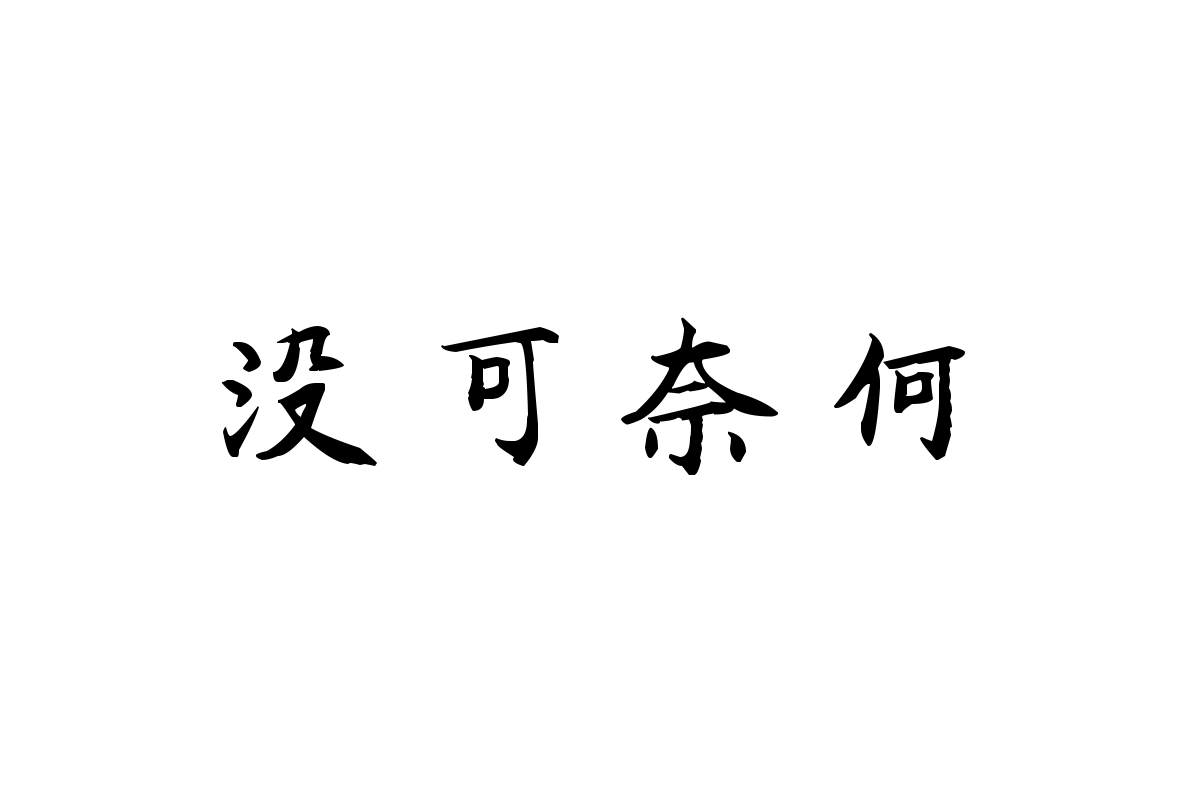
汉呈王天喜花花行楷字体是一种独特的书法风格,融合了王羲之的行楷风格和天喜花的艺术特点。这种字体的特点是笔画流畅、结构严谨,既有王羲之行书的灵动飘逸,又有天喜花的繁复精致。
汉呈王天喜花花行楷字体的特点如下:
1. 字形结构:汉呈王天喜花花行楷字体的字形结构紧凑而不失灵动,笔画粗细适中,既有王羲之行书的力度感,又不失天喜花的细腻感。
2. 笔画特点:汉呈王天喜花花行楷字体的笔画特点鲜明,如“一”字的横画较长,竖画较短;“二”字的撇画较长,捺画较短;“三”字的撇画较长,捺画较短等。这些笔画的特点使得整个字体既有王羲之行书的灵动性,又不失天喜花的繁复性。
3. 结构特点:汉呈王天喜花花行楷字体的结构特点在于其平衡性和对称性。每个字的左右两边都有一定的距离,使得整个字体看起来既稳定又富有变化。同时,每个字的内部也有一定的空间,使得整个字体看起来既饱满又简洁。
4. 艺术特点:汉呈王天喜花花行楷字体的艺术特点在于其对王羲之行书和天喜花的融合。在保持王羲之行书的灵动飘逸的同时,又融入了天喜花的繁复精致,使得整个字体既有传统书法的韵味,又不失现代审美的时尚感。
总之,汉呈王天喜花花行楷字体是一种独特而富有艺术性的书法风格,它既体现了王羲之行书的灵动飘逸,又展现了天喜花的繁复精致,是书法爱好者值得学习和欣赏的一种字体。